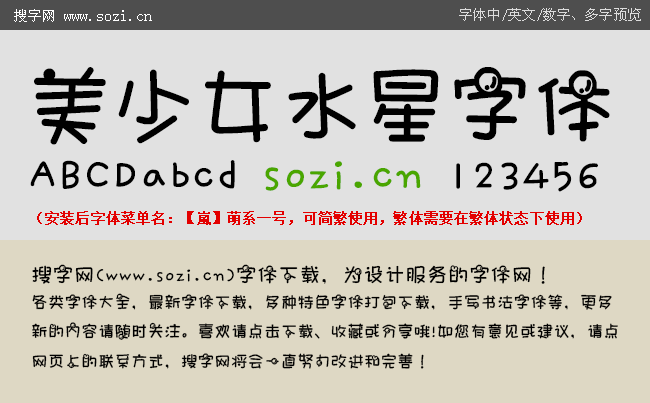
美少女水星字體
搜字網(wǎng)給大家提供一款卡通手寫(xiě)風(fēng)格的手機(jī)中文字體下載。名字叫美少女水星字體,這款手機(jī)字體是仿照兒童手寫(xiě)風(fēng)格的卡通手寫(xiě)字體,結(jié)構(gòu)帶有POP字體風(fēng)格,字體間還插入了大量有趣卡通圖案,特別適合喜歡手機(jī)字體個(gè)性一些的朋友在手機(jī)上安裝使用。